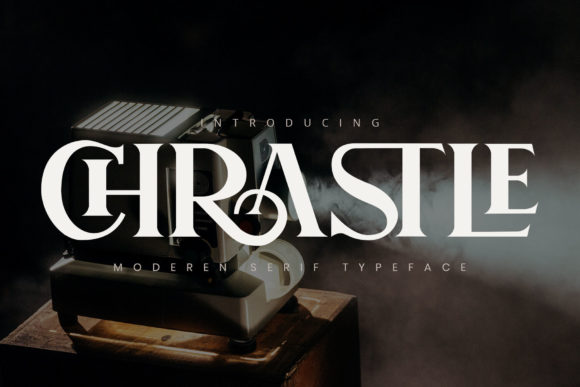
Chrastle - это смСлый ΠΈ ΡΡ‚ΠΈΠ»ΡŒΠ½Ρ‹ΠΉ ΡˆΡ€ΠΈΡ„Ρ‚ с засСчками. Π‘ΠΌΠ΅Π»ΠΎ добавляйтС Π΅Π³ΠΎ Π² свои ΠΏΡ€ΠΎΠ΅ΠΊΡ‚Ρ‹, ΠΈ Π²Ρ‹ Π±ΡƒΠ΄Π΅Ρ‚Π΅ Π² восторгС ΠΎΡ‚ Ρ€Π΅Π·ΡƒΠ»ΡŒΡ‚Π°Ρ‚ΠΎΠ².